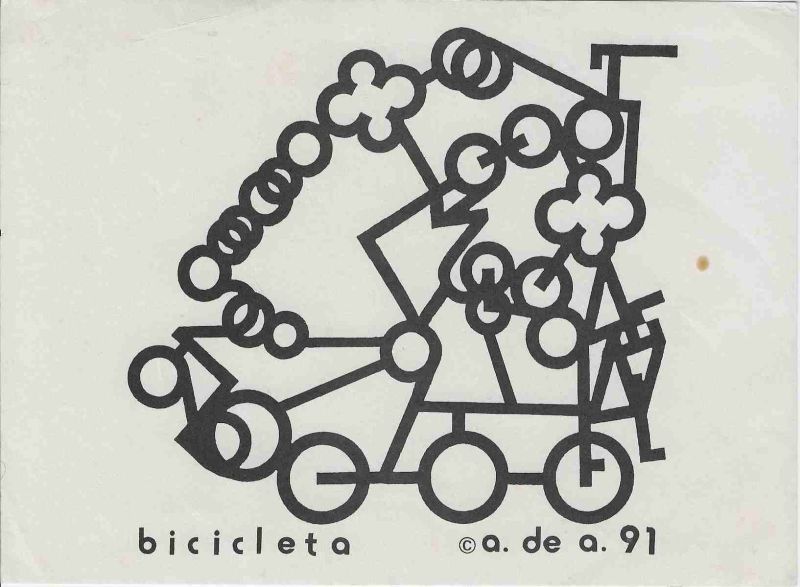
Bicicleta é uma impressão gráfica de Avelino de Araújo realizada em 1991, vinculada à poesia visual, à poesia experimental, à arte conceitual, à tipografia e às investigações intersígnicas relacionadas ao campo do Poema Processo.
Bicicleta é uma impressão gráfica de Avelino de Araújo realizada em 1991, vinculada à poesia visual, à poesia experimental, à arte conceitual, à tipografia e às investigações intersígnicas relacionadas ao campo do Poema Processo. A composição apresenta a imagem de uma bicicleta construída por meio da combinação de letras, números, círculos, linhas, sinais gráficos e formas geométricas. Em vez de desenhar o veículo de maneira convencional, Avelino de Araújo utiliza caracteres tipográficos como módulos visuais para formar rodas, quadro, guidão, selim, pedais, correntes e outras partes mecânicas. A palavra transforma se em imagem e os elementos do alfabeto deixam de exercer apenas função verbal para atuar como componentes estruturais de um objeto reconhecível. Três grandes círculos aparecem na região inferior e funcionam como rodas ou mecanismos de movimento, enquanto diversas formas circulares menores se distribuem pela composição como engrenagens, elos, articulações e pontos de conexão. Linhas retas e diagonais unem esses módulos e sugerem o quadro, os suportes e as hastes da bicicleta. Na região superior, uma sequência de círculos e formas curvas cria uma cadeia semelhante a corrente, percurso ou movimento contínuo. Alguns sinais lembram flores, trevos, parafusos, molas, rodas dentadas e peças mecânicas. A composição explora a relação entre corpo, máquina, deslocamento, equilíbrio e linguagem. A bicicleta depende da articulação entre diferentes partes, assim como a leitura depende da associação entre sinais. Cada caractere possui identidade própria, mas participa de uma estrutura coletiva maior. A obra também pode ser compreendida como metáfora da poesia visual, na qual letras, números e símbolos deixam sua posição habitual e passam a circular por novas funções e sentidos. A repetição das formas circulares sugere rotação, continuidade, velocidade e percurso. A estrutura irregular e acumulativa transmite sensação de movimento, improvisação e invenção. O amplo espaço claro ao redor reforça o isolamento da figura e permite que a bicicleta seja percebida como desenho, diagrama, escrita e máquina poética. Na parte inferior aparecem a identificação bicicleta, a marca de autoria a. de a. e o número 91, correspondente ao ano de 1991. Bicicleta integra a produção de Avelino de Araújo dedicada à transformação de sinais tipográficos, objetos cotidianos e estruturas mecânicas em poemas visuais abertos à interpretação. Palavras chave para indexação: Avelino de Araújo, Bicicleta, 1991, impressão gráfica, poesia visual brasileira, poema visual, poesia experimental, arte conceitual, Poema Processo, bicicleta na arte, tipografia experimental, letras como imagem, números na arte, símbolos gráficos, máquina poética, objeto cotidiano, movimento, rotação, engrenagem, corrente, geometria, escrita visual, palavra imagem, texto imagem, semiótica, intersigno, comunicação visual, arte gráfica brasileira, múltiplo gráfico, arquivo de poesia visual, arte brasileira do século vinte.TEXT FOR THE SALSA PROGRAM IN ENGLISH: Bicycle is a graphic print by Avelino de Araújo produced in 1991 and associated with visual poetry, experimental poetry, conceptual art, typography and intersemiotic investigations related to the field of the Poema Processo movement. The composition presents the image of a bicycle constructed through a combination of letters, numbers, circles, lines, graphic signs and geometric forms. Instead of drawing the vehicle conventionally, Avelino de Araújo uses typographic characters as visual modules to form wheels, frame, handlebars, seat, pedals, chains and other mechanical parts. The word becomes image and alphabetic elements cease to perform only a verbal function and begin to operate as structural components of a recognizable object. Three large circles appear in the lower region and function as wheels or mechanisms of movement, while many smaller circular forms are distributed throughout the composition as gears, links, joints and points of connection. Straight and diagonal lines connect these modules and suggest the frame, supports and rods of the bicycle. In the upper region, a sequence of circles and curved forms creates a chain resembling a continuous route or movement. Some signs resemble flowers, clovers, screws, springs, gears and mechanical components. The composition explores relationships among body, machine, displacement, balance and language. A bicycle depends upon the articulation of different parts, just as reading depends upon the association of signs. Each character retains an individual identity while participating in a larger collective structure. The work may also be understood as a metaphor for visual poetry, in which letters, numbers and symbols leave their customary positions and circulate through new functions and meanings. The repetition of circular forms suggests rotation, continuity, speed and travel. The irregular and cumulative structure conveys movement, improvisation and invention. The broad light field surrounding the image reinforces the isolation of the figure and allows the bicycle to be perceived as drawing, diagram, writing and poetic machine. The lower section contains the identification bicicleta, the authorship mark a. de a. and the number 91, corresponding to the year 1991. Bicycle belongs to Avelino de Araújo
Impressão gráfica em tinta preta sobre papel claro, composta por uma grande figura de bicicleta construída com caracteres tipográficos e formas geométricas. A imagem ocupa quase toda a área central da folha. Observam se três círculos de maior dimensão na parte inferior, unidos por linhas horizontais e diagonais. Diversos círculos menores, letras, números, barras, formas triangulares e sinais semelhantes a molas aparecem sobrepostos e conectados. A região superior apresenta uma sequência curva de formas circulares e elementos parecidos com elos de corrente. Na lateral direita aparecem estruturas verticais e angulares que podem ser associadas ao guidão, ao suporte e a outras partes do veículo. Algumas formas se assemelham a flores ou trevos e acrescentam referências orgânicas à construção mecânica. A organização é assimétrica, densa e dinâmica, com diferentes pesos de linha e sobreposição de elementos. Na margem inferior encontra se a palavra bicicleta em letras minúsculas espaçadas, seguida pelo símbolo de autoria, pela identificação a. de a. e pelo número 91. O suporte apresenta leves ondulações, vincos, pequenas manchas, alterações de tonalidade e sinais de envelhecimento e manuseio. A peça pode ser classificada como poema visual, impressão de artista, múltiplo gráfico, desenho tipográfico, composição mecânica e documento conceitual, sendo relevante para pesquisas sobre Avelino de Araújo, Poema Processo, poesia visual, bicicleta, movimento, tipografia, semiótica e produção gráfica brasileira.OBSERVATION TEXT IN ENGLISH: Graphic print in black ink on light colored paper composed of a large bicycle figure constructed from typographic characters and geometric forms. The image occupies most of the central area of the sheet. Three larger circles are visible in the lower section and are connected by horizontal and diagonal lines. Numerous smaller circles, letters, numbers, bars, triangular forms and signs resembling springs appear superimposed and connected. The upper region presents a curved sequence of circular forms and elements resembling chain links. Vertical and angular structures on the right side may be associated with the handlebars, supports and other components of the vehicle. Some forms resemble flowers or clovers and introduce organic references into the mechanical construction. The arrangement is asymmetrical, dense and dynamic, with different line weights and overlapping elements. The lower margin contains the word bicicleta in spaced lowercase letters, followed by the authorship symbol, the identification a. de a. and the number 91. The support presents slight undulations, creases, small stains, changes in tone and signs of aging and handling. The piece may be classified as a visual poem, artist print, graphic multiple, typographic drawing, mechanical composition and conceptual document, making it relevant to research on Avelino de Araújo, Poema Processo, visual poetry, bicycles, movement, typography, semiotics and Brazilian graphic production.
Bicycle is a graphic print by Avelino de Araújo produced in 1991 and associated with visual poetry, experimental poetry, conceptual art, typography and intersemiotic investigations related to the field of the Poema Processo movement.